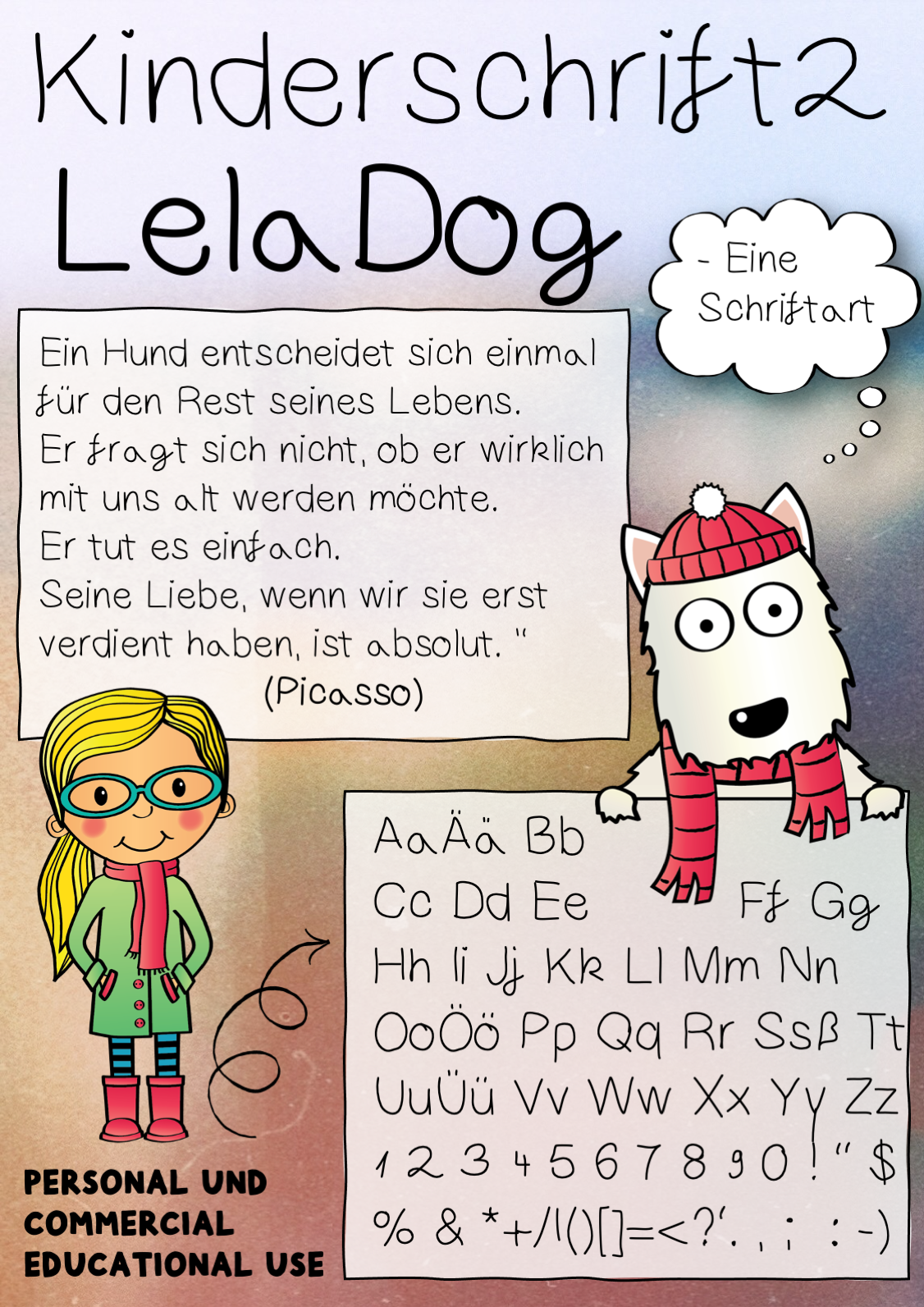
selbst erstellte Schriftarten - Lela Dog - Kinderschrift 2 / Font / Schriftart - Quirlidoodle - Deckblatt
Die zweite Kinderschrift hier :-)
Lela Dog - Kinderschrift 2 / Font / Schriftart